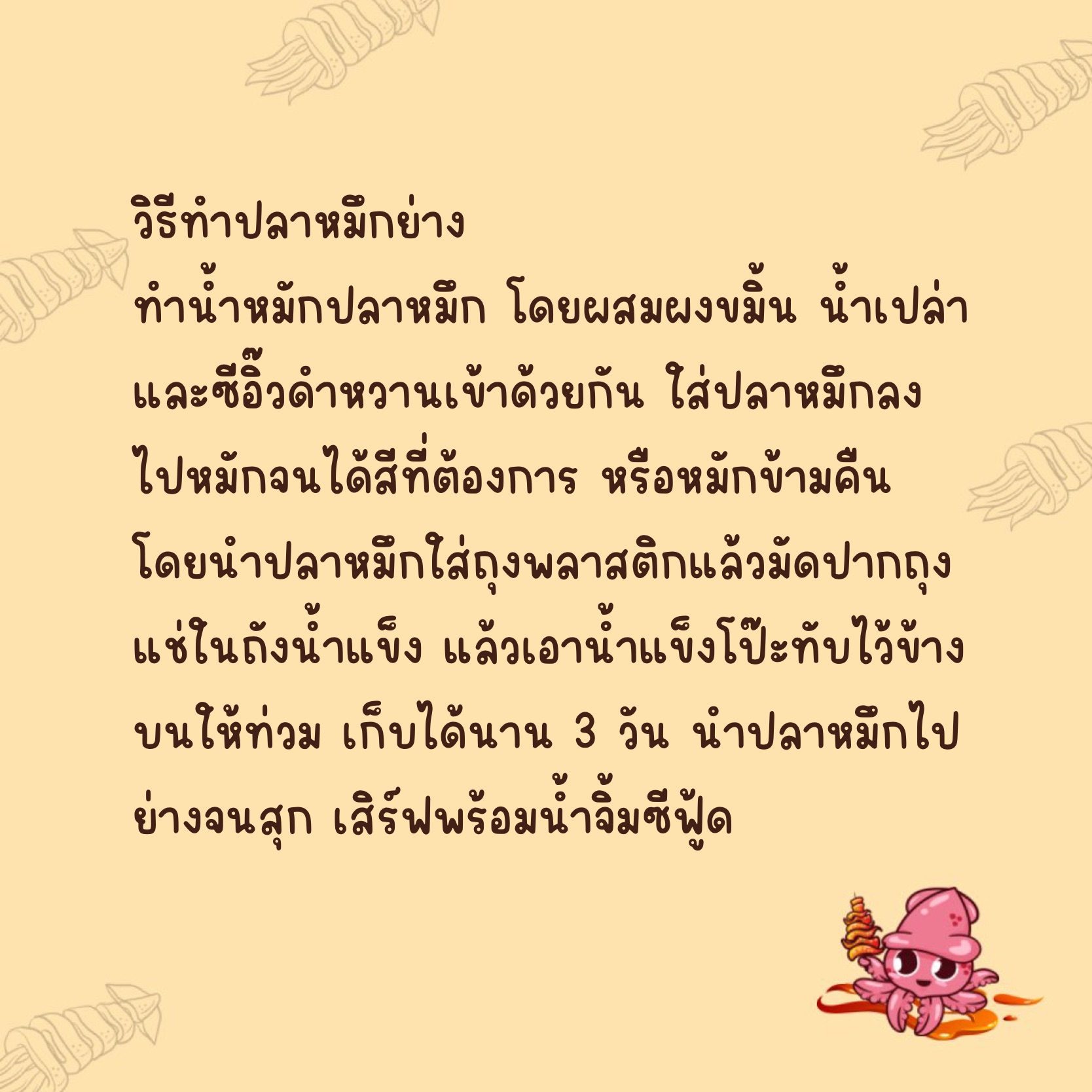
หมึกย่าง (Muekyang)
ฟอนต์ลายมือ หมึกย่าง (Muekyang)
สามารถใช้งานได้หลายรูปแบบไม่ว่าจะเป็น การจดโน็ต สรุปงาน ตกแต่งป้ายสินค้า โปสเตอร์ หรือใช้ตกแต่งรูปภาพ/วิดีโอและโฆษณาสินค้าต่างๆก็ได้เช่นกัน